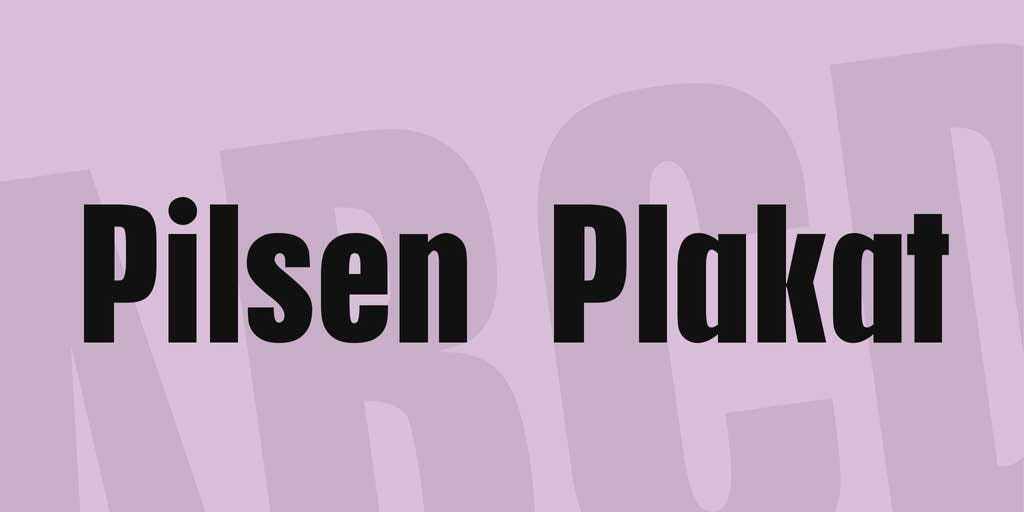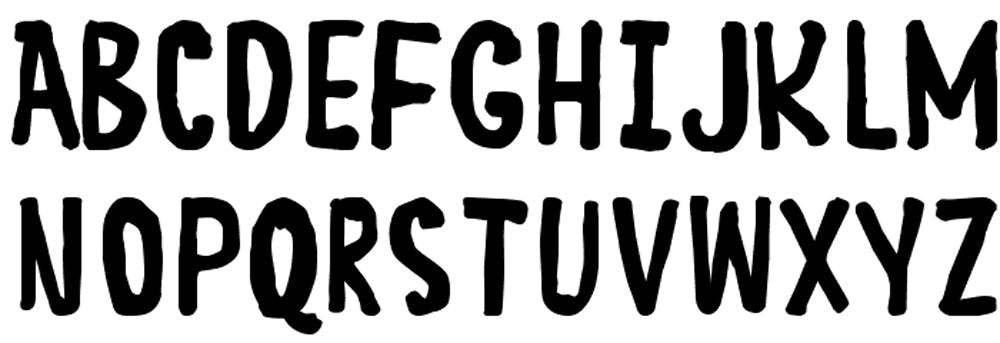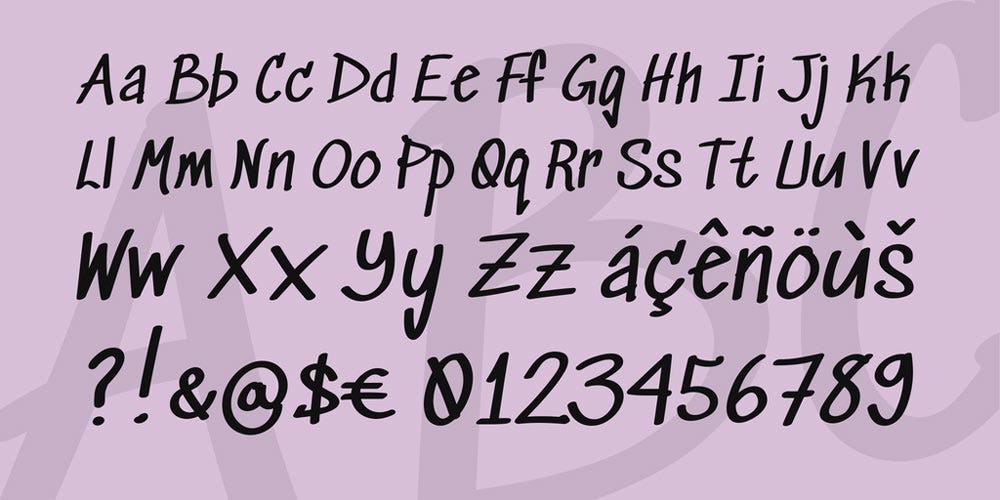
Un menú atractivo brilla aún más con una selección de tipografías para restaurantes que deleitan a primera vista. Si tienes en mente abrir un negocio de comida próximamente o en el 2022, pero no sabes por dónde empezar, ¡no te preocupes! En Crehana queremos ayudarte, así que hemos hecho una colección de fuentes para restaurantes y, así, empieces creando tu logotipo o vayas armando un menú tentativo.
Según el portal web The Fork Manager, dentro del proceso de branding de una marca, el logo es el gran punto de partida. Básicamente, es como el horno para la cocina. En ese sentido, será vital que selecciones una tipografía de comida idónea para tu negocio. Eso sí, también será necesario que aprendas cómo crear un slogan para restaurantes que te ayude a impresionar a tus clientes.
En esta lista encontrarás tipografías de restaurantes gratis, aunque también habrá otras de pago por si decides invertir en una fuente única. Sin más preámbulos, te invitamos a conocer las mejores tipografías para logos de restaurantes y pastelerías.
Así que, ¡alista tu cocina y manos a la masa!
1. Foodpacker
Empezamos con las tipografías para logos de restaurantes con esta impresionante fuente. Si buscabas una tipografía para logos de restaurantes que sea divertida y original, Foodpacker es la indicada. Destaca por sus simpáticos y divertidos trazos, además de su gran legibilidad. Está disponible en mayúsculas, minúsculas, números y caracteres especiales.
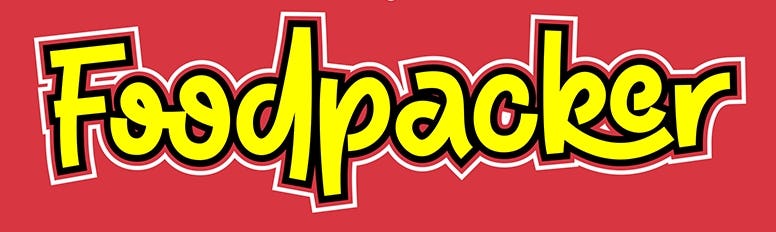
2. Cunia Free Font
Cunia es de las tipografías para restaurantes por excelencia debido a su minimalismo (una tendencia de diseño gráfico muy popular hoy en día) y a sus interesantes formas redondeadas. Disponible en mayúsculas y números.
3. Modeka Free Font
Siguiendo con la tendencia minimalista, Modeka es una tipografía para logos de restaurantes modernos y sofisticados. También tiene esquinas redondeadas, pero con un estilo más elegante. Disponible en mayúsculas, minúsculas, números y caracteres especiales.
4. Braxton
Si quieres darle un toque original al logotipo de tu restaurante, Braxton es la fuente que estabas buscando. Esta tipografía para restaurantes tiene un estilo en cursiva que no hará más que darle mucha sofisticación a tu logotipo.
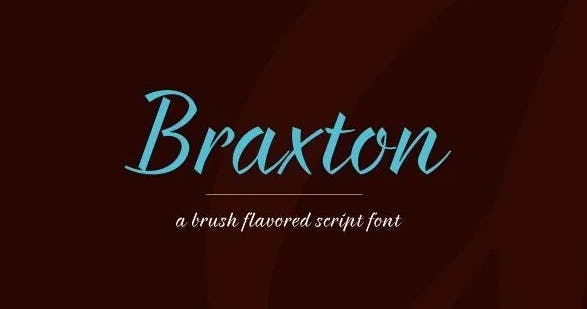
5. Maxwell
Maxwell es una tipografía de estilo sans serif que pertenece a Doublezero y que destaca por su legibilidad, su onda casual y elegante al mismo tiempo. Sin duda, esta es una de las tipografías para restaurantes que le transmitirá a tus clientes la tranquilidad de almorzar o cenar como en casa.
6. Olivia
¿Te gusta la caligrafía perfecta? Entonces, Olivia es la tipografía para restaurantes ideal. Con esta fuente podrás darle clase y sofisticación a tu restaurante, dos aspectos fundamentales para que tus clientes se sientan a gusto y te recomienden una y otra vez.
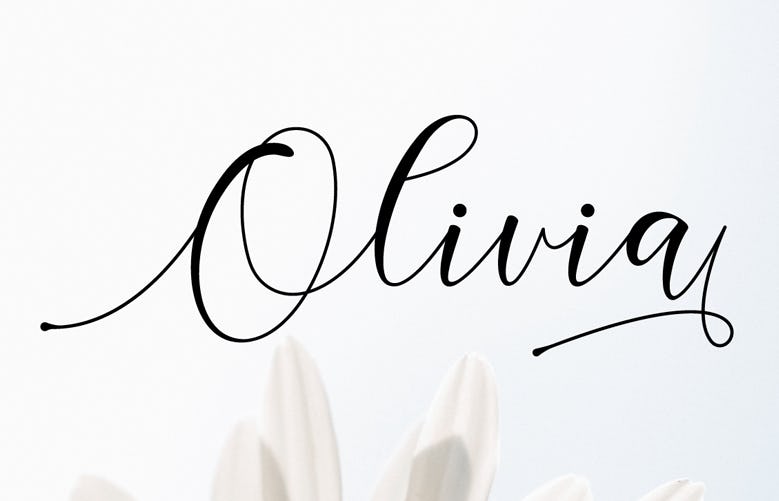
7. Glamora
Si el concepto de tu restaurante está basado en el glamour, el logotipo debe demostrarlo. Glamora es una tipografía para restaurantes que transmite exclusividad. Está disponible en dos estilos (Regular y Stencil), así como en mayúsculas y minúsculas.
8. Long Johnson
Long Johnson es una tipografía para restaurantes audaces debido a la peculiaridad de su estilo, que se caracteriza por sus letras alargadas y por estar disponible únicamente en mayúsculas. En definitiva, se trata de una de las tipografías para restaurantes más divertidas y que quedará grabada en la mente de tus clientes.
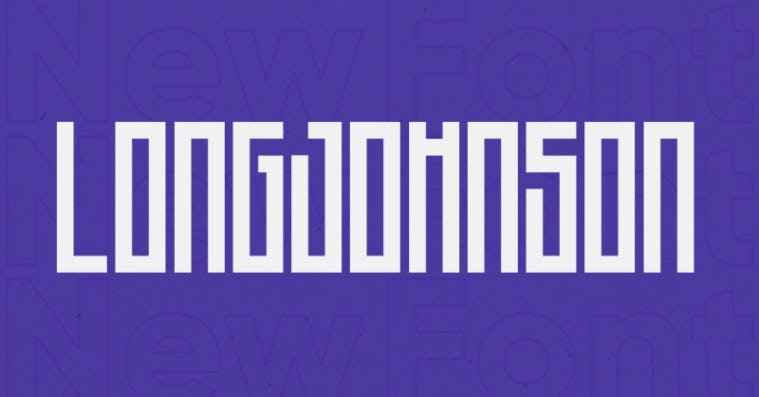
9. Poiret One
¿Cómo darle un toque único y especial al logotipo de tu restaurante? Con un recurso bastante sencillo: mezclar líneas y curvas. Poiret One es una tipografía para restaurantes que, precisamente, ofrece aquella combinación simétrica que le dará a tu marca una elegancia única en su especie. Disponible en mayúsculas, minúsculas, números y algunos caracteres especiales.
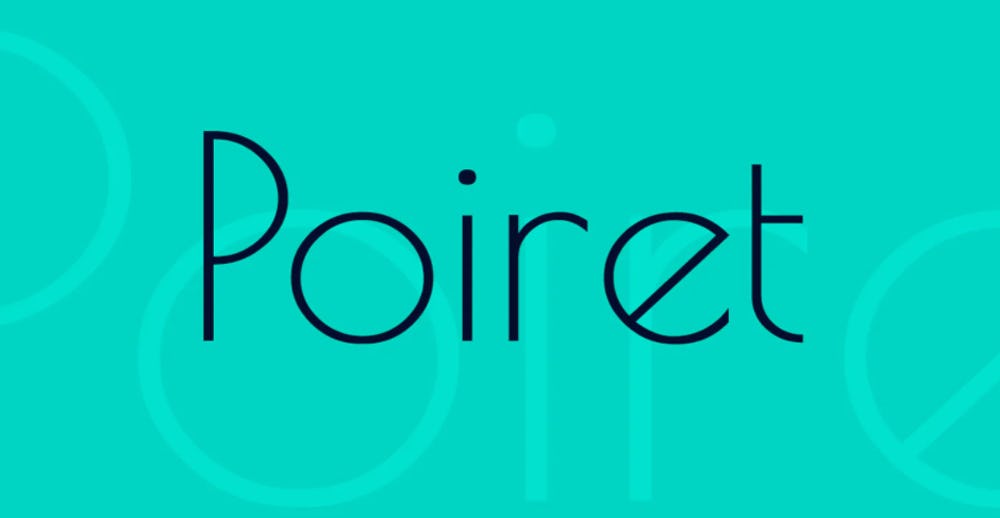
10. Barista Script
En caso le quieras dar un aspecto vintage a tu restaurante, esta fuente de letras para restaurantes es la indicada. Barista es de las tipografías para logos de restaurantes que destaca por su originalidad al portar elementos que le darán un aspecto único a tu logotipo.
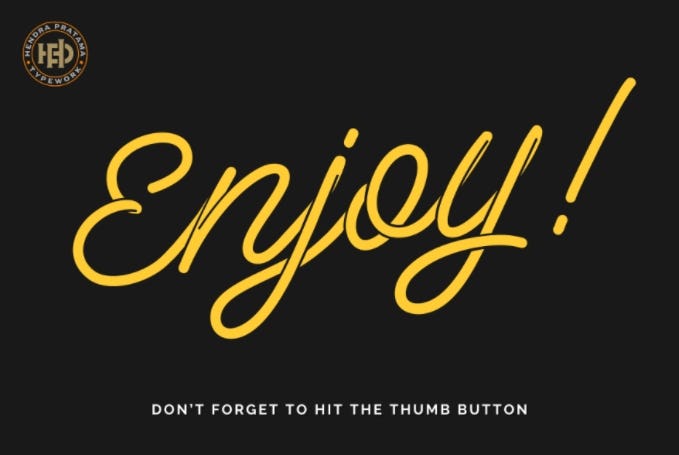
11. Insaniburger
¿Y qué mejor que abrir un negocio sobre un platillo tan popular como las hamburguesas? Insaniburger es una de las tipografías para restaurantes que deleitará a los clientes con tan solo ver tu logo. De hecho, los mejores restaurantes de hamburguesas no solo deslumbran a sus visitantes con sus tradicionales recetas, sino también a través de sus creativas tipografías, ya sea plasmadas en la carta o como parte de su decoración.
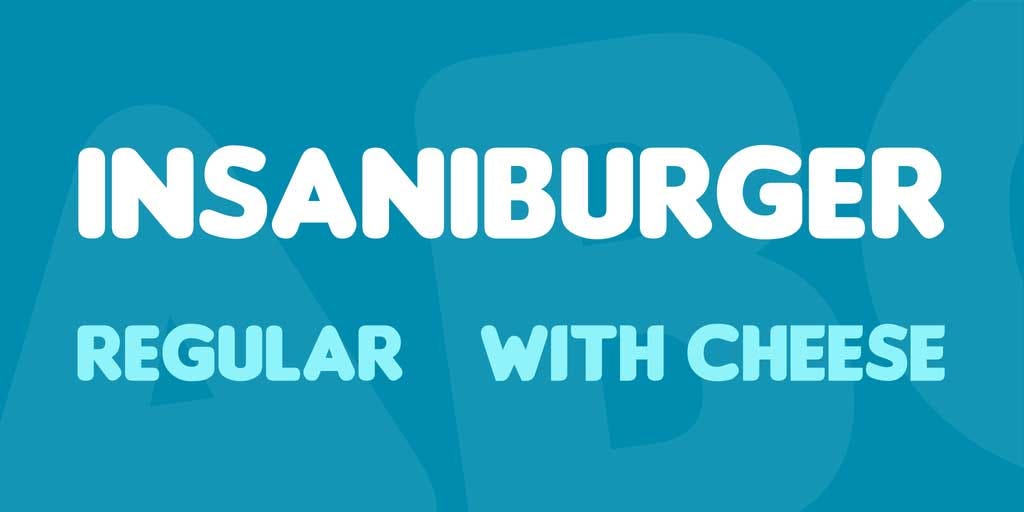
12. Popular café
En estas tardes frías de invierno, nada mejor que acompañarnos con un delicioso café, ¿cierto? Si piensas lanzar tu propia cafetería, entonces esta tipografía para restaurantes, sin duda, impresionará a tus clientes. Una fuente para restaurante inspirada en los carteles diseñados de una famosa cafetería de Londres, conocido como - ¿puedes adivinarlo? - El Café Popular. Está disponible en mayúsculas, números y algunos caracteres especiales.
Como menciona Cástor Vera, profesor del curso online de diseño de logotipos desde cero, debes diseñar una tipografía que se convierta en un icono de la cultura popular. Al respecto, menciona lo siguiente:
“El logotipo debe sumar a la marca y las personas puedan reconocerlo fácilmente, así como recordarlo en su día a día”.